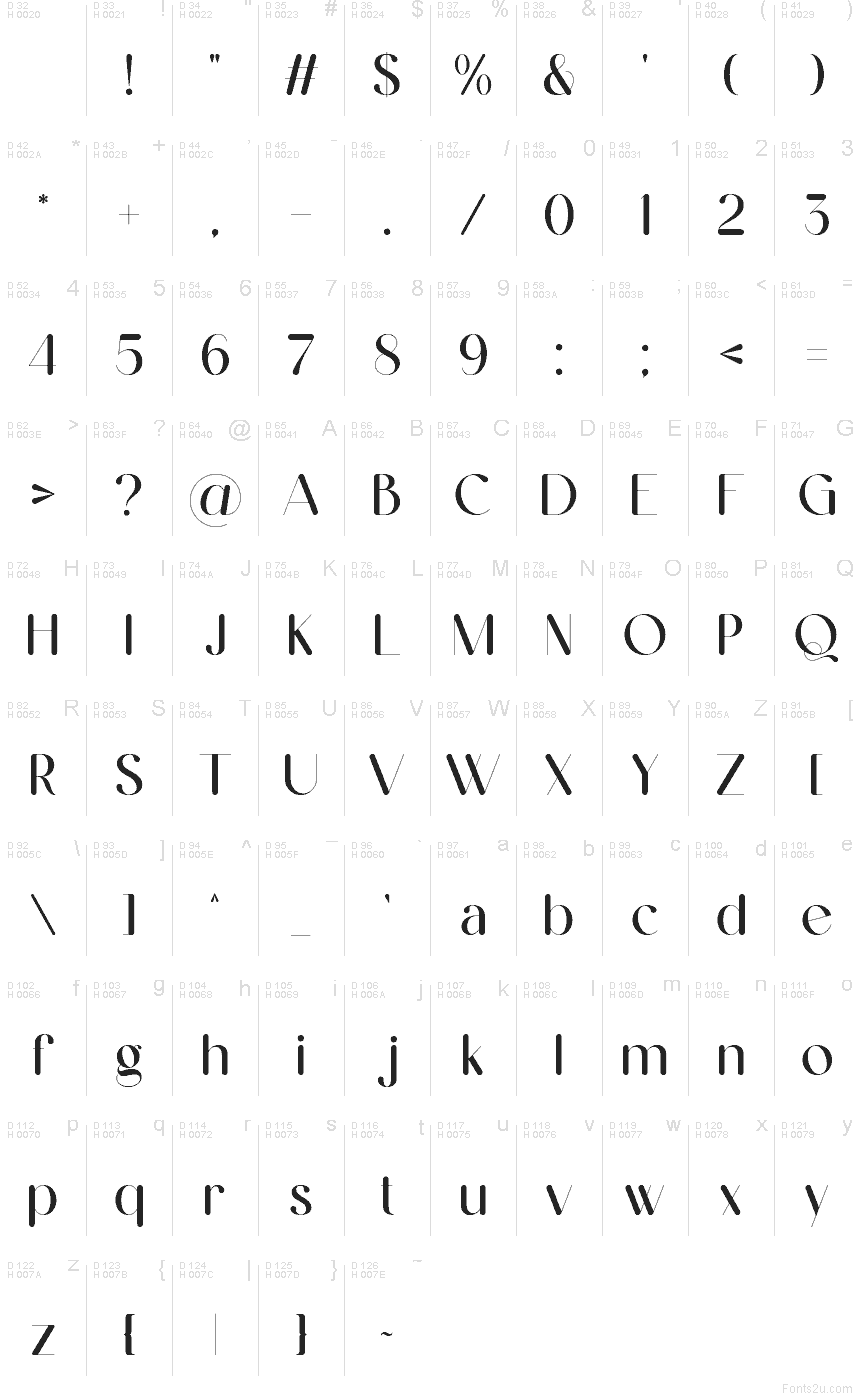
Maqive, do Ermedia Studio, é uma fonte sem serifa gratuita de alto contraste, com um perfil elegante e voltado à moda. Curvas amplas e traços verticais espessos encontram barras transversais finíssimas, proporcionando às letras uma dramática variação de espessura. Diversas formas são invulgarmente altas e abertas.
Usada como uma voz editorial refinada, ela se adequa a capas de revistas de moda, embalagens de produtos de beleza e cartazes de galerias, onde suas formas arredondadas e fluidas dialogam com uma fotografia límpida ou ilustrações minimalistas. O contraste pronunciado entre traços grossos e finos conecta essas aplicações ao branding de luxo, setores que se benefician de uma tipografia que parece feita sob medida, e não corporativa.